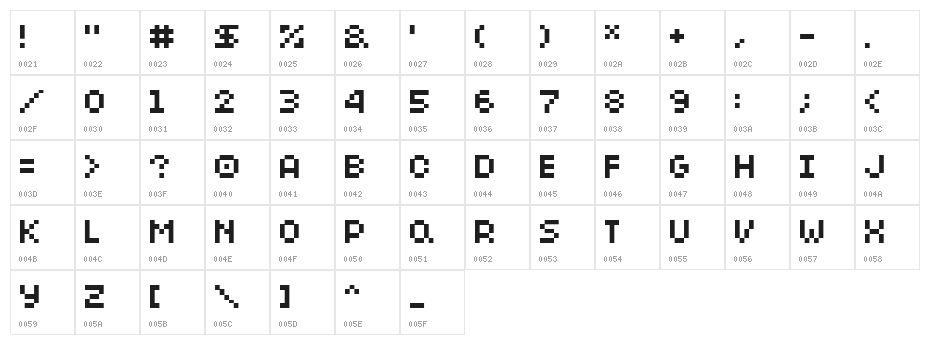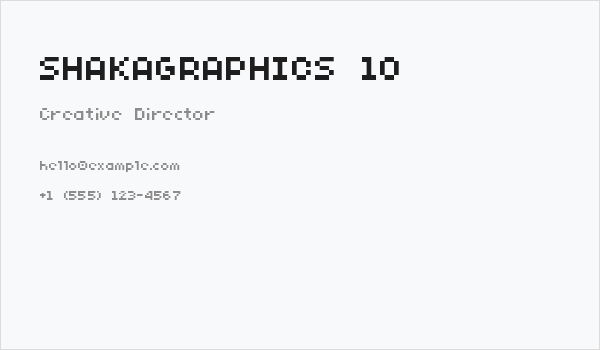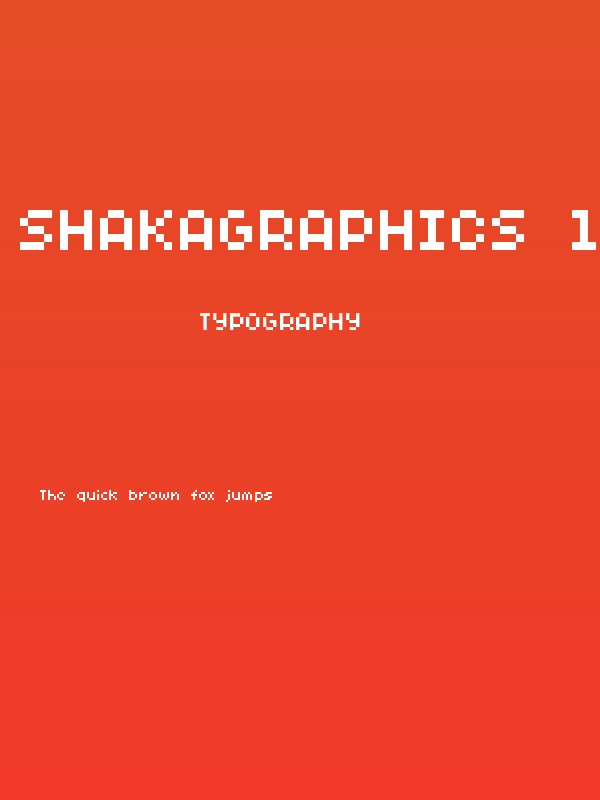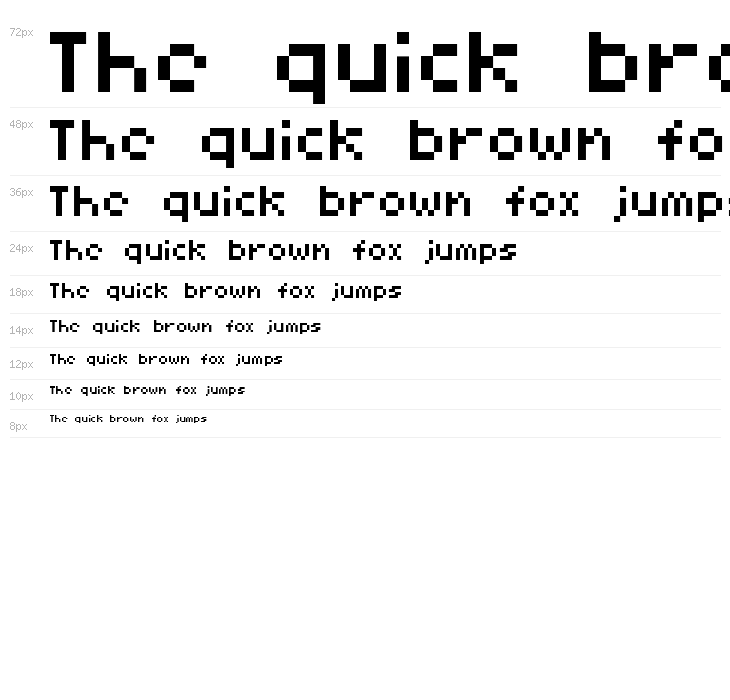
SHAKAGRAPHICS 10 Font
| Gesamtstil | Retro, Digital |
| Anwendungsfall | Logos, Headlines, Posters |
| Vorgeschlagene Projekte | Ideal for retro video game designs, digital art projects, tech-themed posters, and nostalgic branding. |